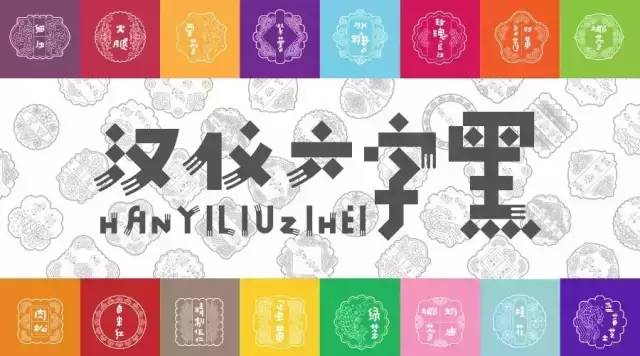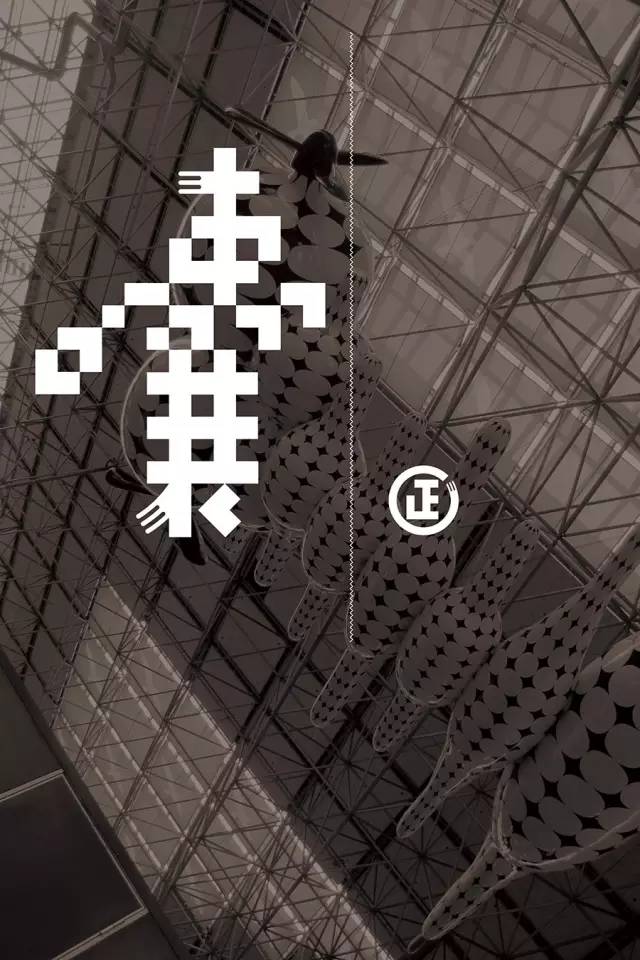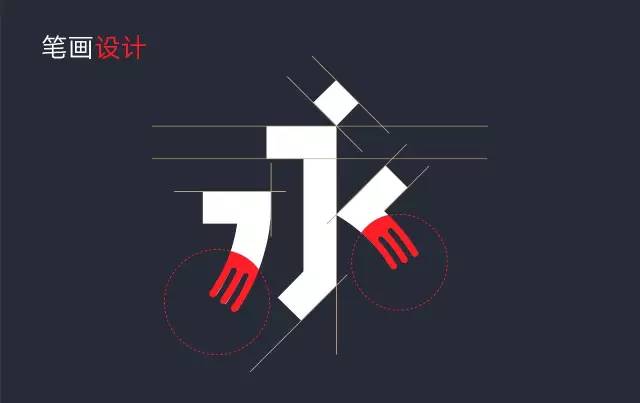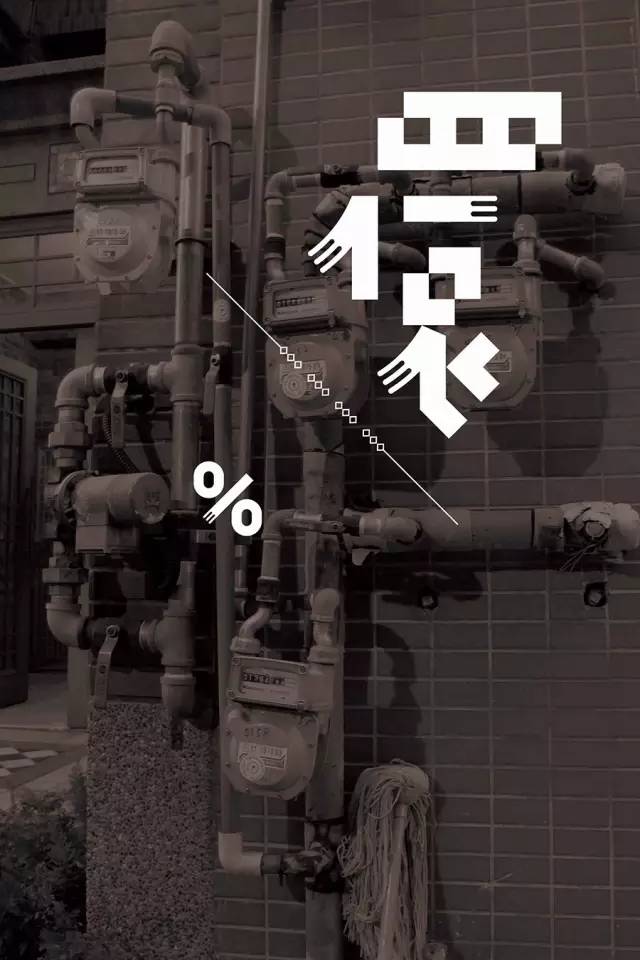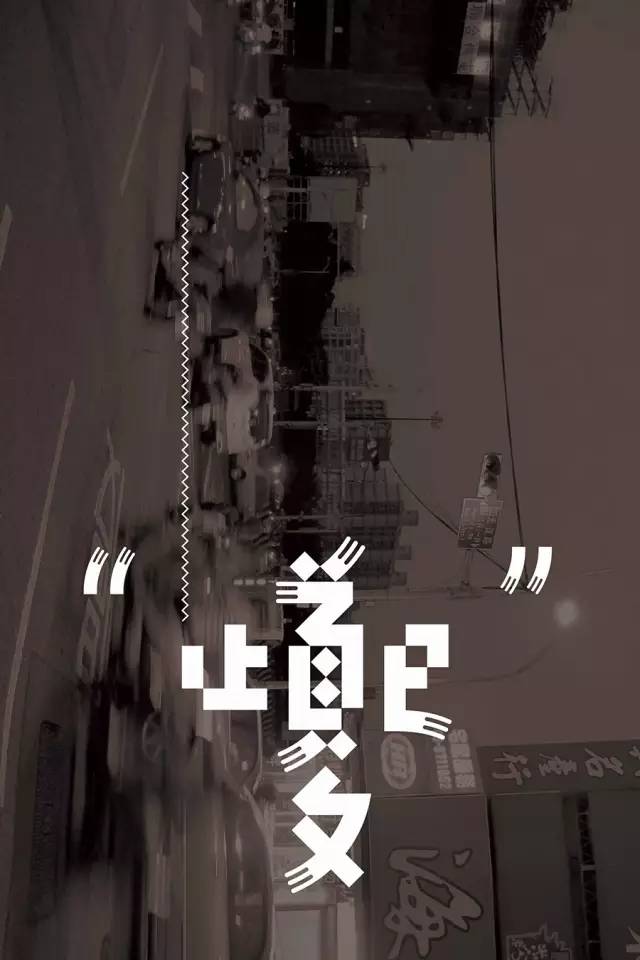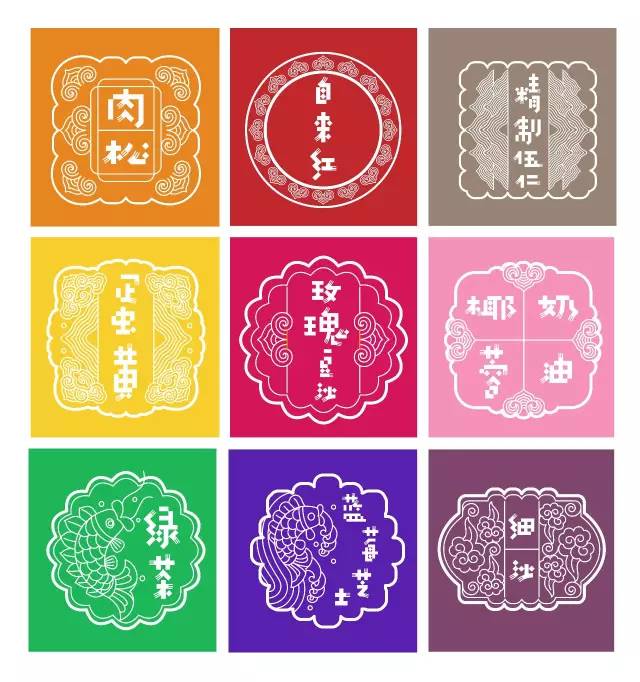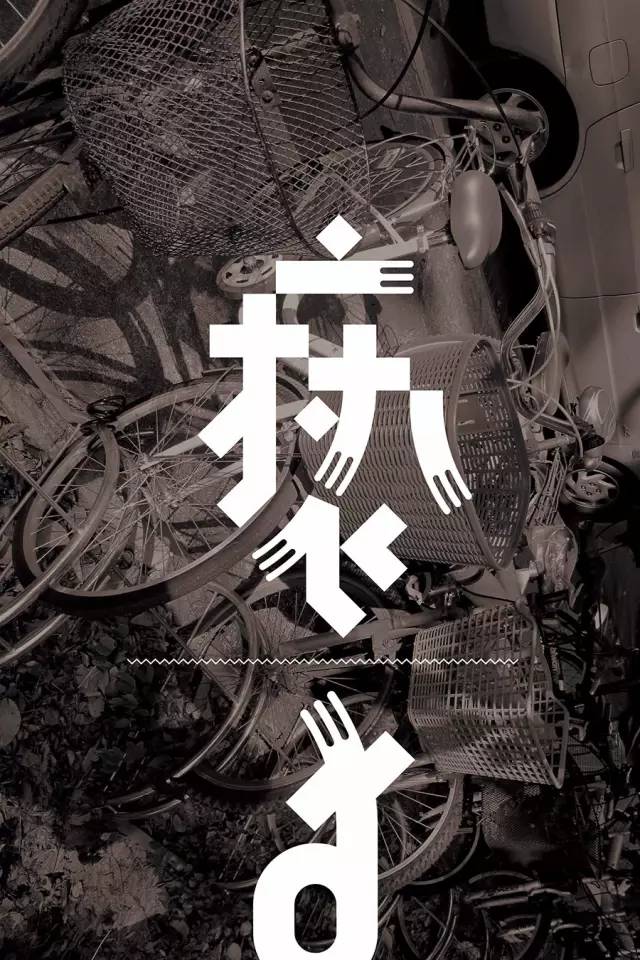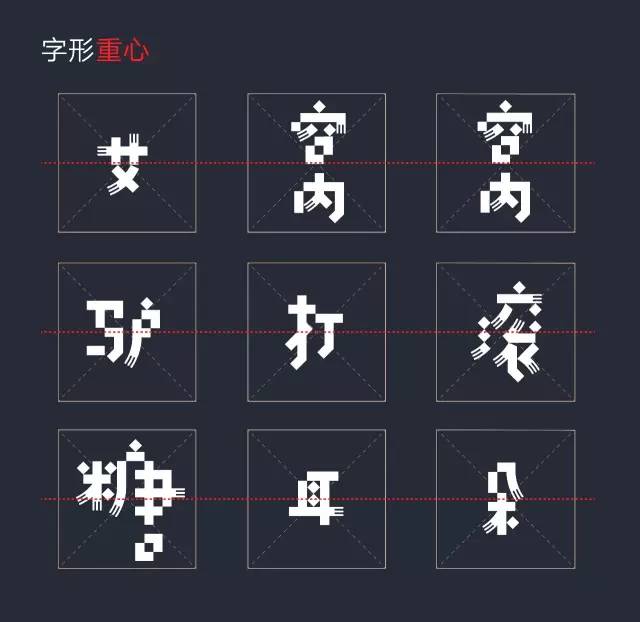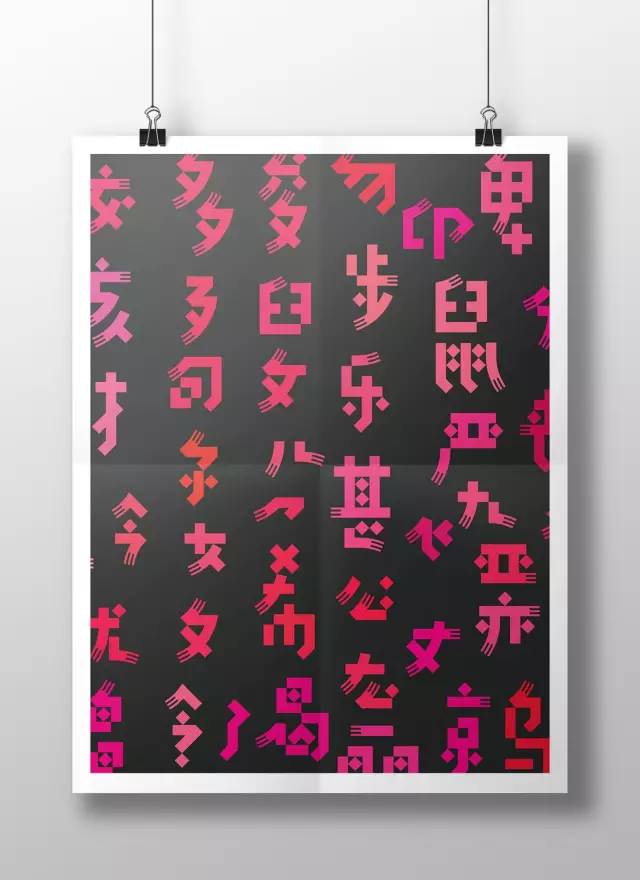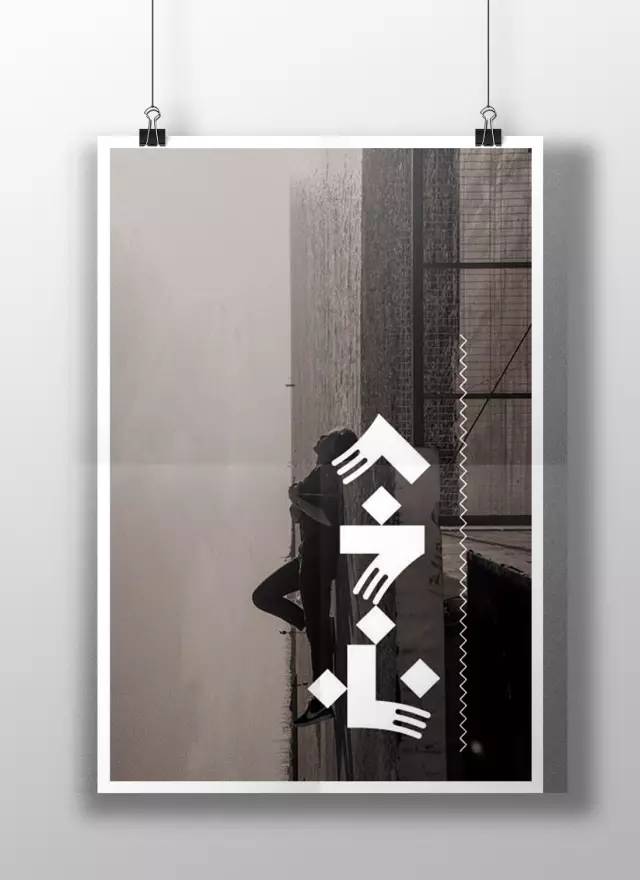
不满意路边小店招牌上严肃到家的黑体、宋体,也不能接受随手涂鸦到了疯狂程度的错字、丑字,这大概就是六字黑的设计初衷。
“六字”字体的笔形是单调、机械、规矩的几何形体,但组合关系是复杂、险要、矛盾、失衡的罕见结构状态。并融入大量的即兴处理的不可控因素。请相信这些不是,也不可能是预先考虑好的。而是经过800个字的信手摆放以后才逐渐形成的出乎意料的结构体系。
——主创设计师 岳昕
笔画设计
“围巾”or“叉子”,这款被归属于“黑体”的字体,有着遵循黑体等宽笔画的特点,但不同的是每个字都有一个可爱的“小尾巴”。
结构设计
重心平稳,反传统,字距变宽,不拘一格。
应用环境
快乐?多变?趣味?
游戏?美食?旅行?
有快乐因子的地方,就有六字黑
但一定记住一点,
六字黑作为典型的标题字,
并不适合大量文字排版,
所以在用的时候,
一定不要超过六个字哦:)
此版本符合国标GB2312-80(国标中文简体)
共计6763个汉字
应用欣赏